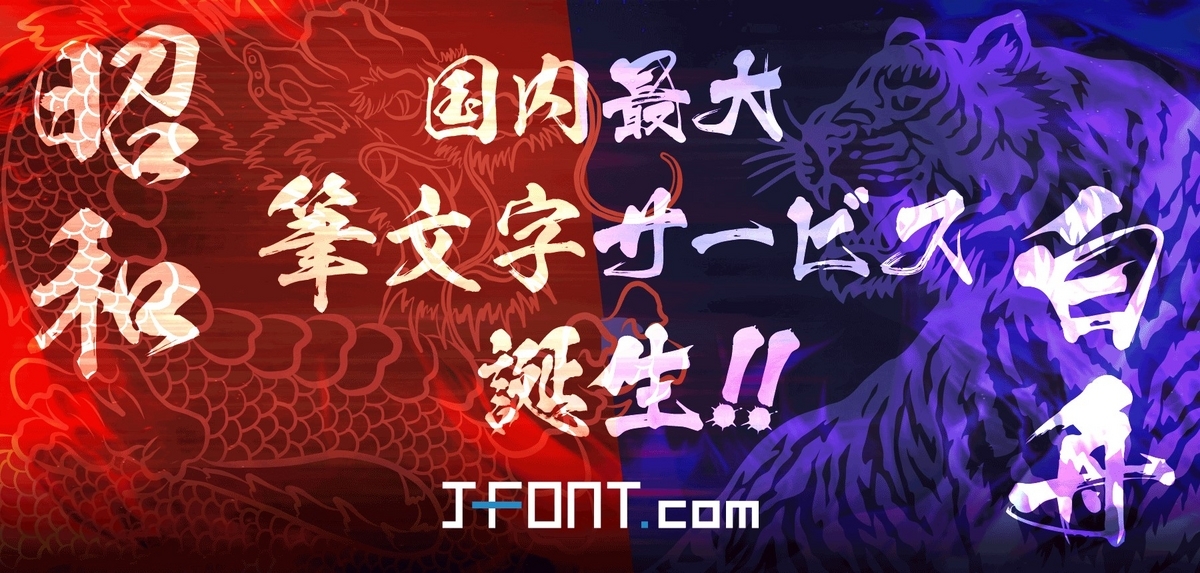
筆文字メーカーたちが競演する究極筆文字サービス爆誕!シヤチハタ×白舟書体のJ-Font.comに昭和書体合流!シヤチハタ×白舟書体×昭和書体
シヤチハタは、フォントサービス事業「J-Font.com(ジェイフォントドットコム)」に筆文字フォントメーカー「株式会社昭和書体」が参画したことを2023年3月3日に発表した。
「J-Font.com」は、広告媒体やメディア、プロモーション活動や書籍、デジタルコンテンツなどに幅広く使えるフォントを提供するフォントサービス事業で、標準フォントとは一味違う迫力ある筆文字フォントに特化することで、「筆文字=J-Font.com」を目標にサービスを強化してきた。
この度、「白舟書体」の筆文字フォントに加えて、「昭和書体」の豊富なラインナップが合流することになり、「J-Font.com」は、国内2大筆文字フォントメーカーが揃えた唯一無二の筆文字プラットフォームに進化を遂げる。
「J-Font.com」に昭和書体が加わったことで、より多くのフォントをJ-Font.comから選択できるようになるため、さまざまなデザインの雰囲気に合わせた筆文字フォントを選びやすくなる。
昭和書体
広告看板事業を起源として生まれた毛筆書体フォントの専門メーカー。直筆感覚にこだわり、正に手書きテイストのフォントを提供することで、日本の文化である毛筆書体を未来永劫に守り続けていく。
▼書体見本(一部)